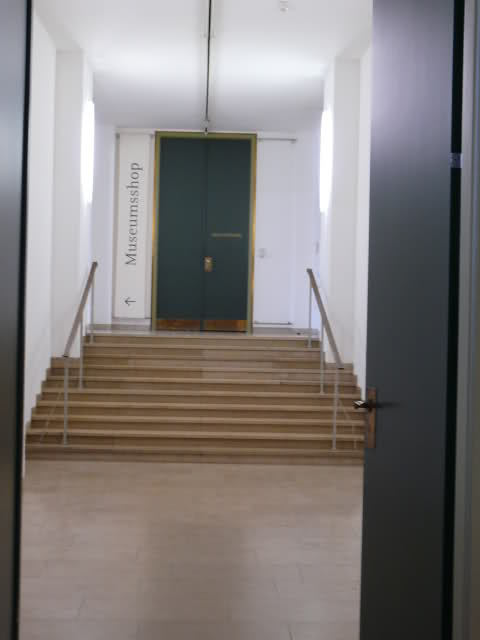
Wie heißt das?
ich wüßte gerne ob die so gestaltete Textfahne, Bild von mir im Anhang, einen speziellen Namen hat. Also ob es einen Namen dafür gibt, daß die Schrift senkrecht nach oben zu lesen ist, bzw. das die Schrift um 90 Grad nach links gedreht ist. Ist blöd zu erklären, deshalb dachte ich es gibt vielleicht einen Namen dafür. Falls ich jetzt eine doofe Frage gestellt habe, sorry, bin einfach noch am lernen, bei diesem Thema. :cry: Das Foto habe ich übrigens in der Alten Pinakothek in München gemacht. Die Schrift ist eine spezielle Version der Frutiger next. Habe ich soweit "herausgegoogelt".
Also, ob es einen Namen dafür gibt, dass die Schrift senkrecht nach oben zu lesen ist, bzw. dass die Schrift um 90 Grad nach links gedreht ist.
Gestürzte Schrift?
Das Foto habe ich übrigens in der Alten Pinakothek in München gemacht. Die Schrift ist eine spezielle Version der Frutiger next. Habe ich soweit »herausgegoogelt«.
Mit daraufgetackerten Serifen? Glaube ich jetzt nun wirklich nicht. Und Frutiger Serif kann’s eigentlich auch nicht sein. Aber das war ja eh nicht die Frage.
Stimmt, die Schrift auf der Fahne kann nicht Frutiger next sein, verstehe nur nicht wieso. Im ganzen Haus sind Schilder und auch Plakate mit der "Hausschrift" und die sind nach Aussage der Leute dort Frutiger next. Die haben auch sonst das ganze Infomaterial mit der gleichen Schrift, da ich jetzt mit ´zig Fotos aus ´zig Museen hantiere bin ich froh dass du das gesehen hast. Denn ich habs definitv nicht gesehen. :roll: Wobei ichs wirklich rätselhaft finde warum die das gemacht haben.
Ich würde das als senkrechten Banner bezeichnen.